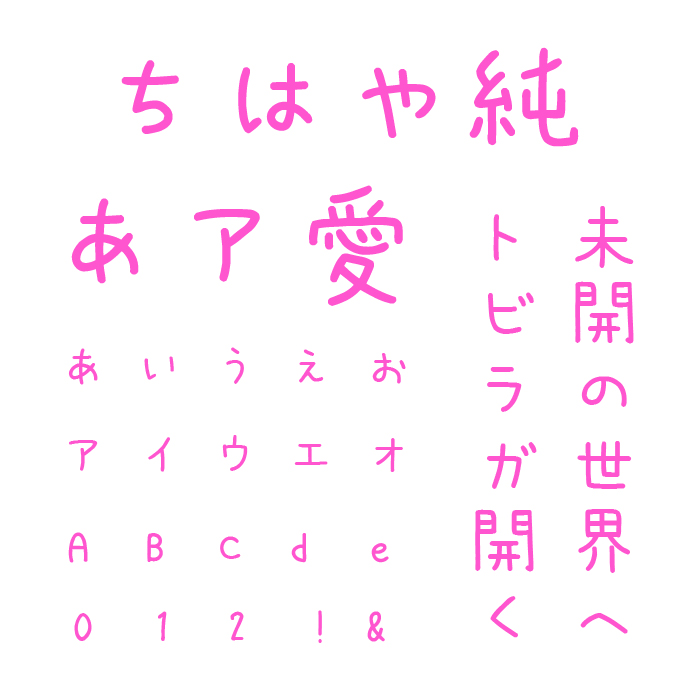
ちはや純は、ひらがな・カタカナを中心に丸みを帯びたシンプルで素朴な手書き風フォントです。
小さい子が丁寧に書いたような、どこか幼さとやさしさを感じさせるデザインで、読む人にほっこりとするあたたかな印象を与える手書きフォントです。力が抜けた自然体の文字が、親密で等身大な雰囲気が愛らしいです。
育児ブログや絵日記、エッセイなど、素直な感情を伝えるコンテンツに特におすすめな、やさしい手書きフォントです。
収録文字は、漢字・ひらがな・カタカナ・アルファベット・数字・記号が収録。